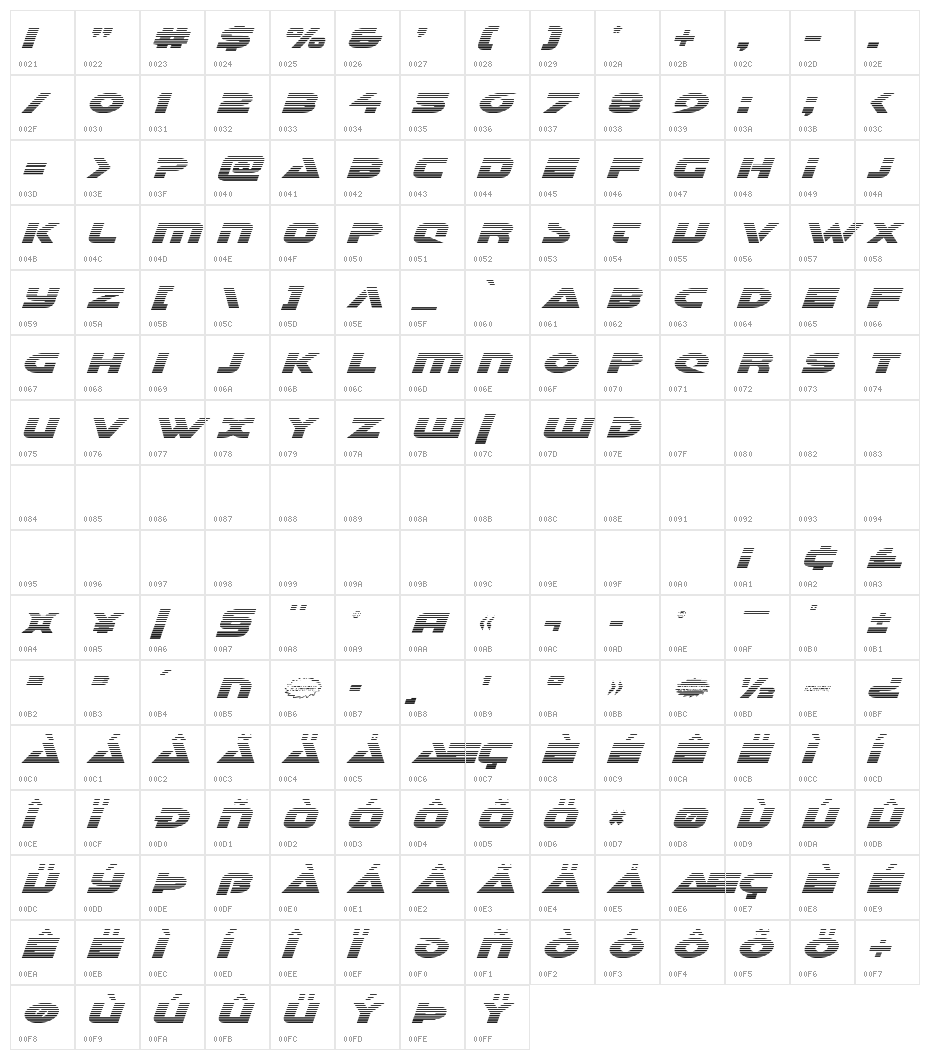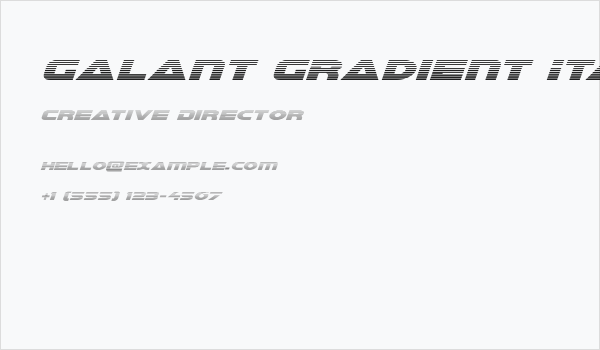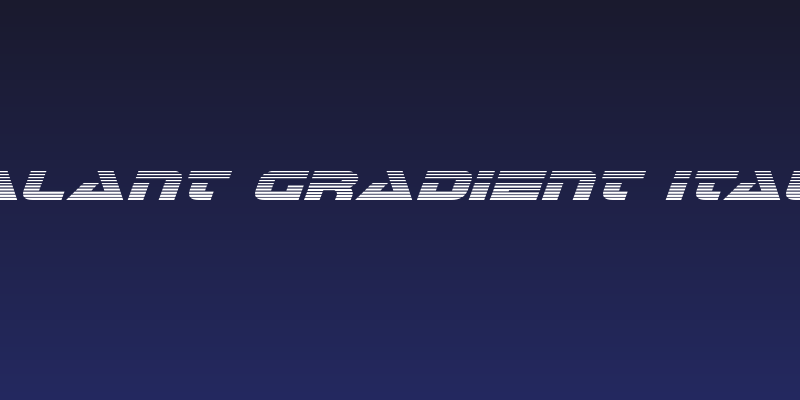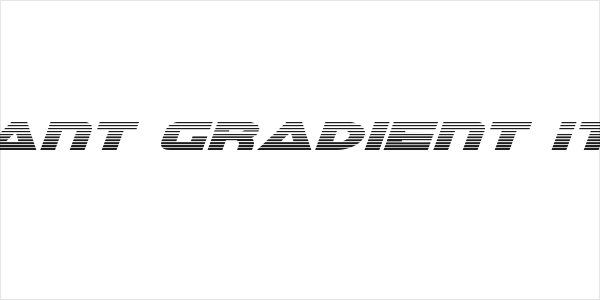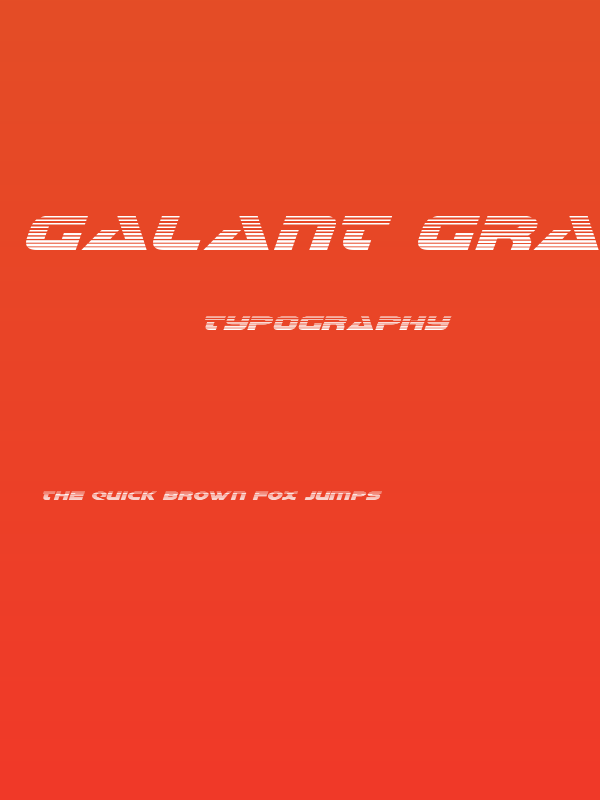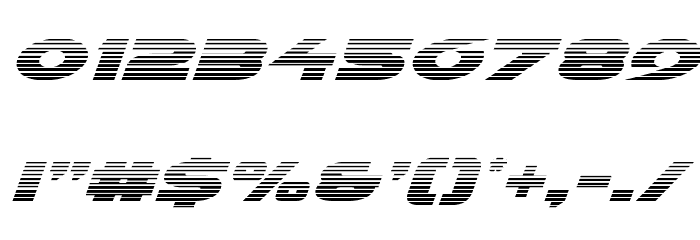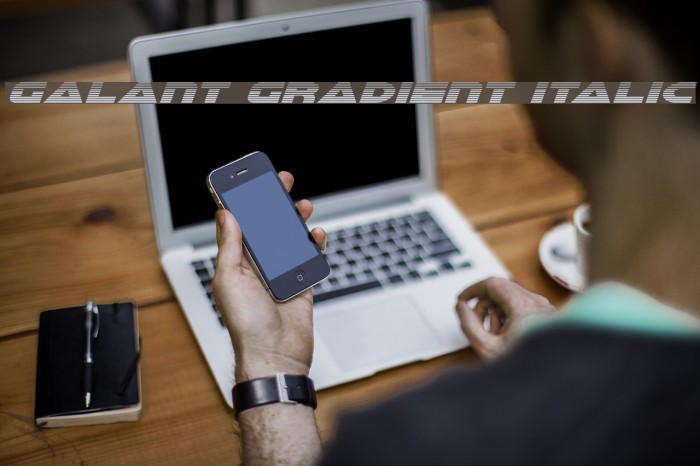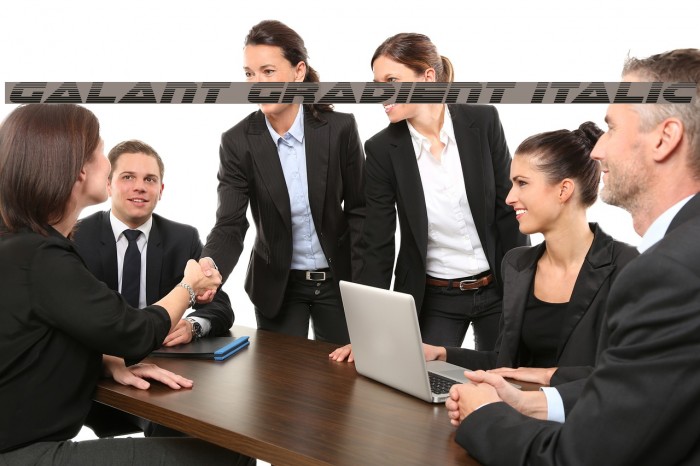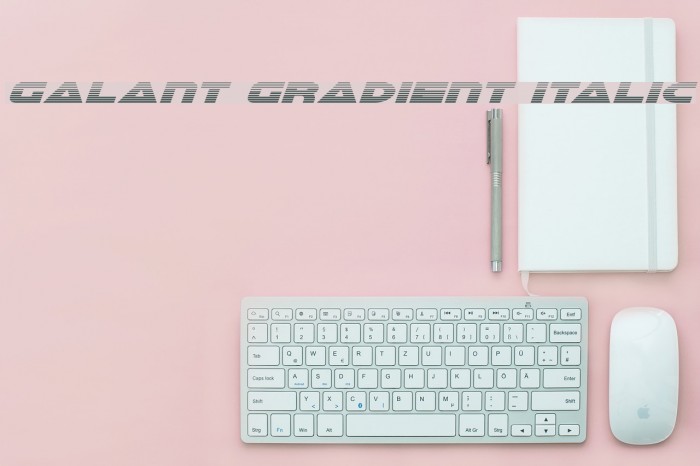
Galant Gradient Italic Font
Iconian Fonts - Daniel Zadorozny - www.iconian.com
| Vorgeschlagene Projekte | Ideal for futuristic branding, tech-related projects, digital art, and eye-catching headlines. |